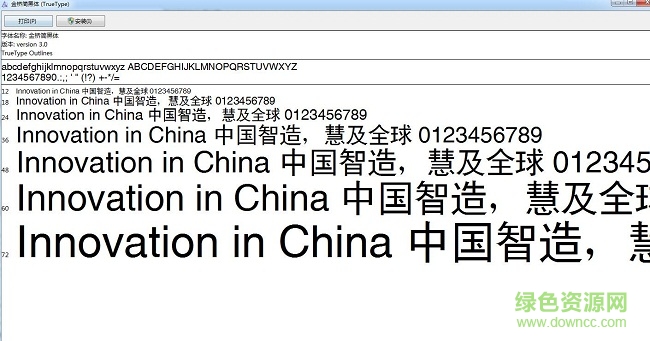
jqheitijt字體又叫金橋簡黑體,是一款黑白均勻的常用字體,這款字體清晰度高,簡潔大方,適合用于各種宣傳導(dǎo)語,能給人留下強烈的印象,有需要者歡迎免費下載!
1.相對于宋而言,黑體字的橫豎筆畫的粗細(xì)要相對一直,“人工設(shè)計”的效果也更強,常被用于作為“力量較強的效果”和“時尚的效果”的處理!
2.相對于黑體而言,宋體字的字體更像是用筆書寫出來的,這種字體的手寫體的感覺更強烈,多用于文字量較大,有希望讀者能夠平靜閱讀下去的文章中!